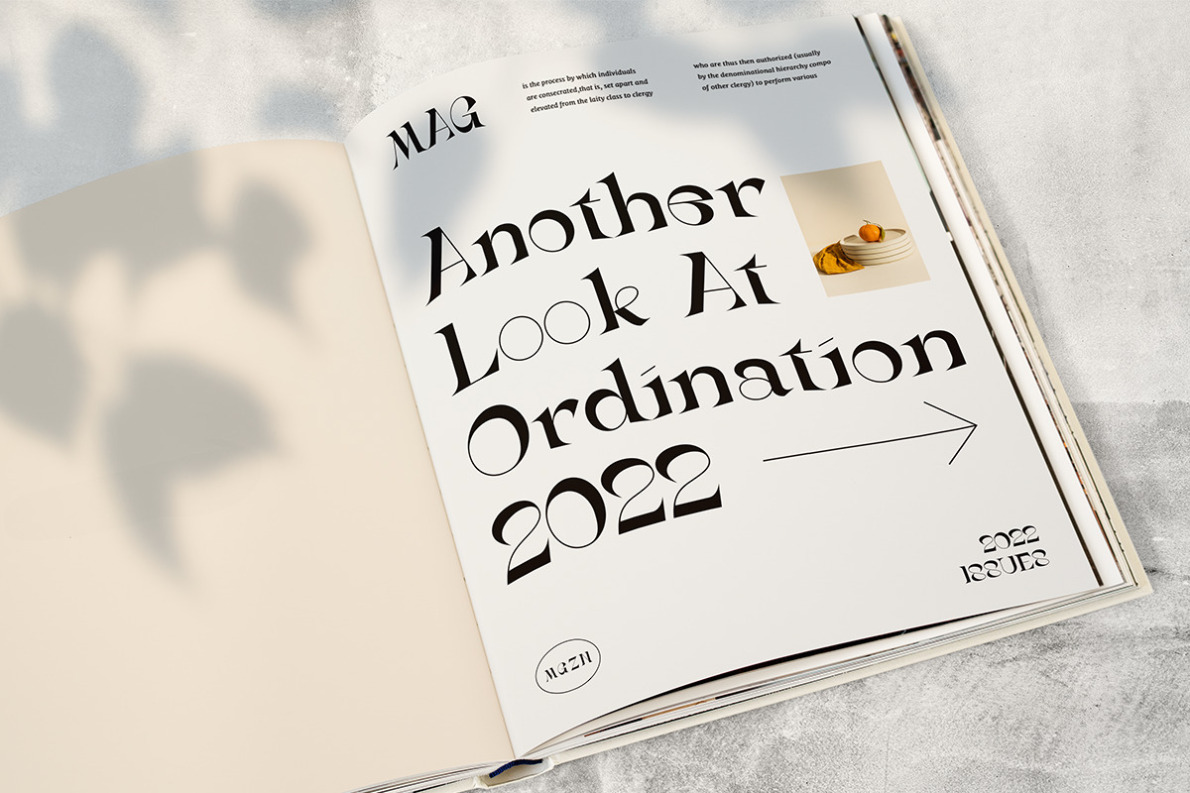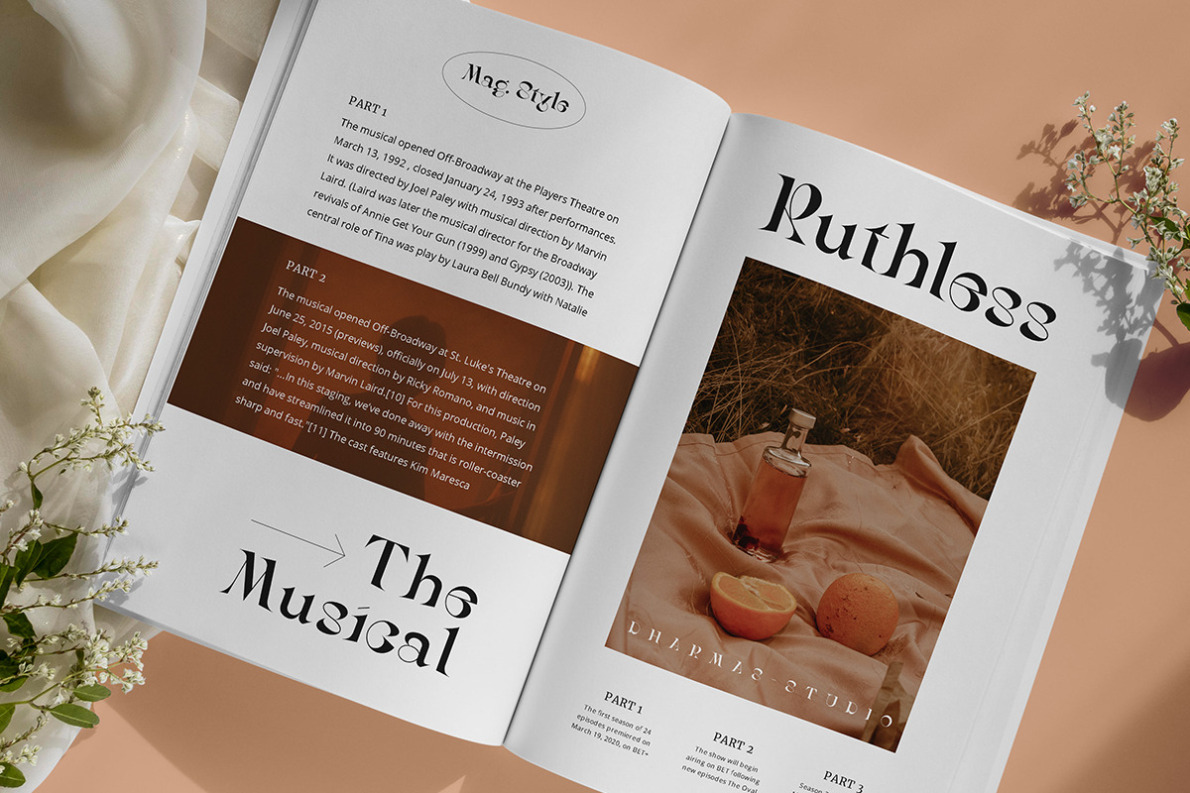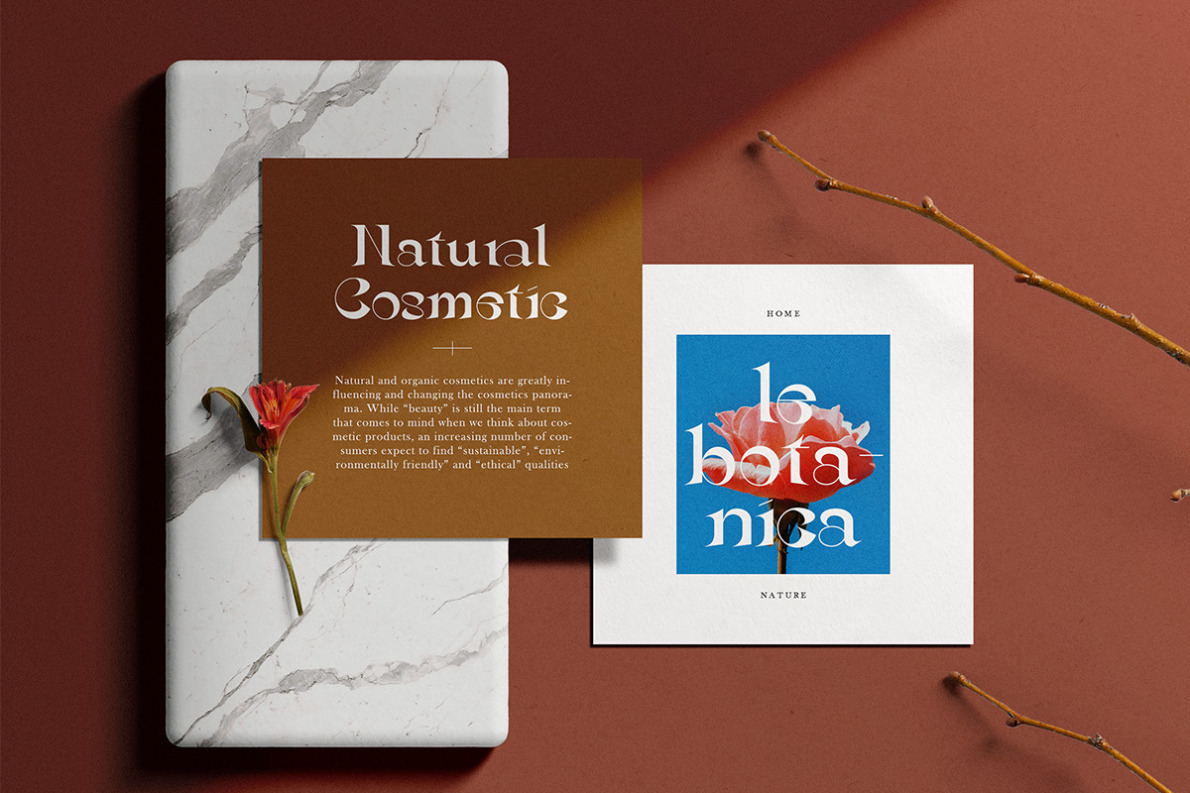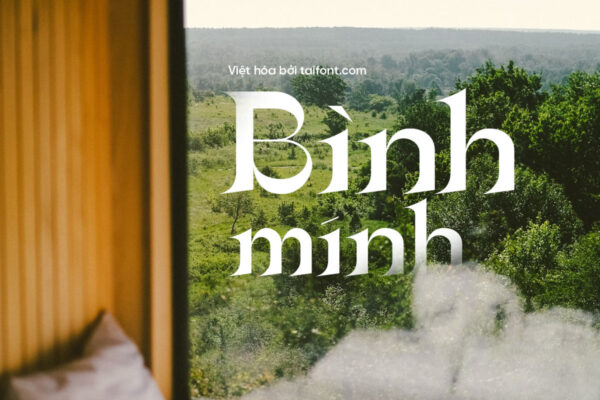
Giới thiệu về Font TF Seraya Việt hóa
TF Seraya Việt hóa là một font chữ có chân (serif) mang vẻ đẹp tinh tế và đầy sang trọng. Với những đường nét được thiết kế tỉ mỉ, thanh mảnh nhưng vẫn giữ được sự rõ ràng, Seraya toát lên phong thái đẳng cấp và sự thanh lịch vượt thời gian, rất phù hợp cho những thiết kế cao cấp.
Font này là lựa chọn lý tưởng để tạo nên sự ấn tượng và chuyên nghiệp, đặc biệt là trong các ấn phẩm đòi hỏi tính thẩm mỹ cao:
- Thiết kế tạp chí sang trọng: Hoàn hảo cho các tạp chí thời trang, nghệ thuật, kiến trúc, hoặc các ấn phẩm cao cấp khác. Seraya giúp các tiêu đề, bài viết, hoặc các phần nội dung trở nên cuốn hút, chuyên nghiệp và dễ đọc, nâng tầm đẳng cấp của tạp chí.
- Thiết kế thời trang và mỹ phẩm: Phù hợp cho các thương hiệu muốn thể hiện sự tinh tế, độc quyền và phong cách xa xỉ trên bao bì, nhãn mác, hoặc các ấn phẩm quảng bá.
- Thiết kế nhận diện thương hiệu: Có thể dùng để tạo logo và các yếu tố thương hiệu mang phong cách cổ điển, sang trọng và có chiều sâu.
Với TF Seraya Việt hóa, bạn có thể dễ dàng tạo ra những thiết kế không chỉ đẹp mắt mà còn truyền tải được thông điệp về sự tinh tế, sang trọng và đẳng cấp, nâng tầm giá trị cho mọi dự án của mình.